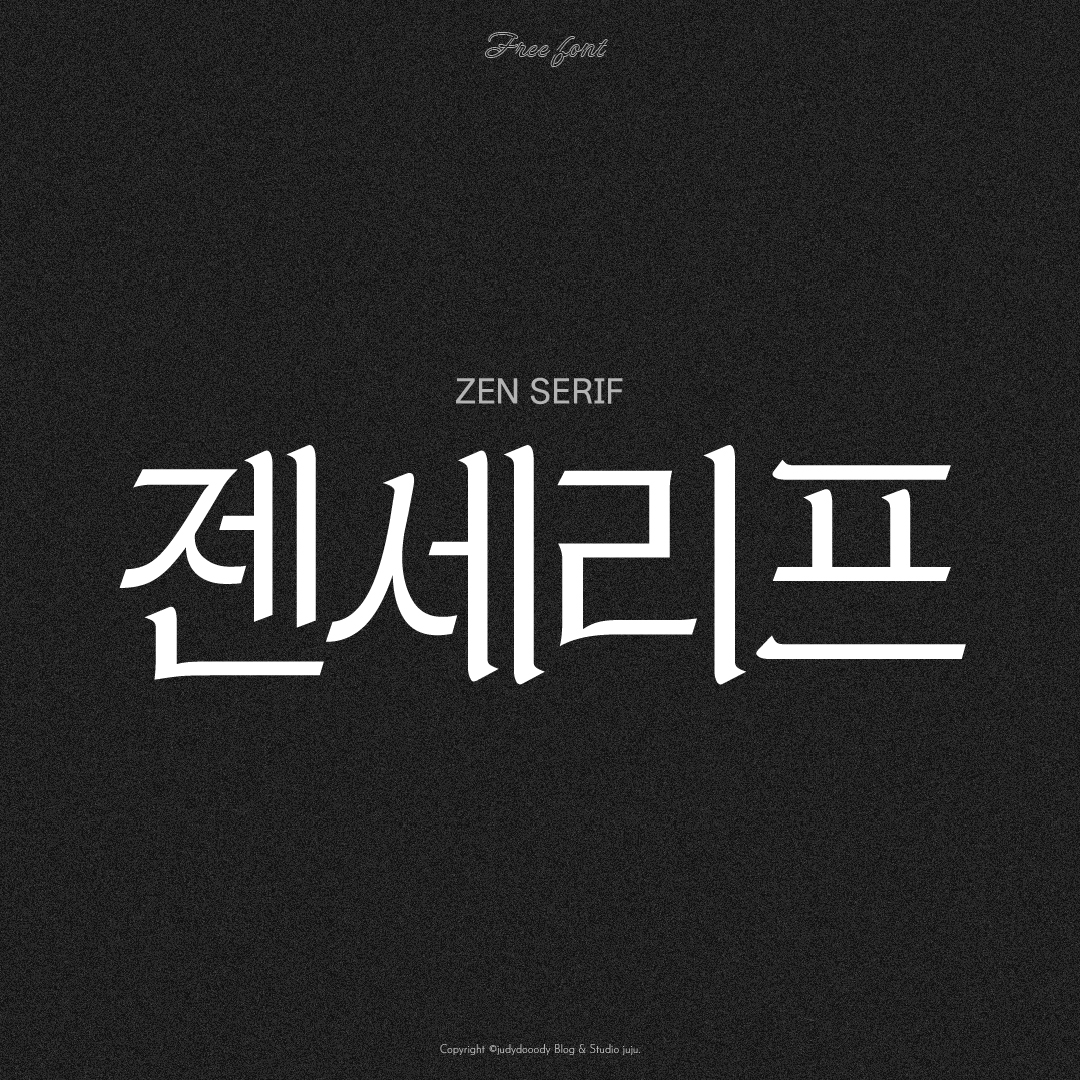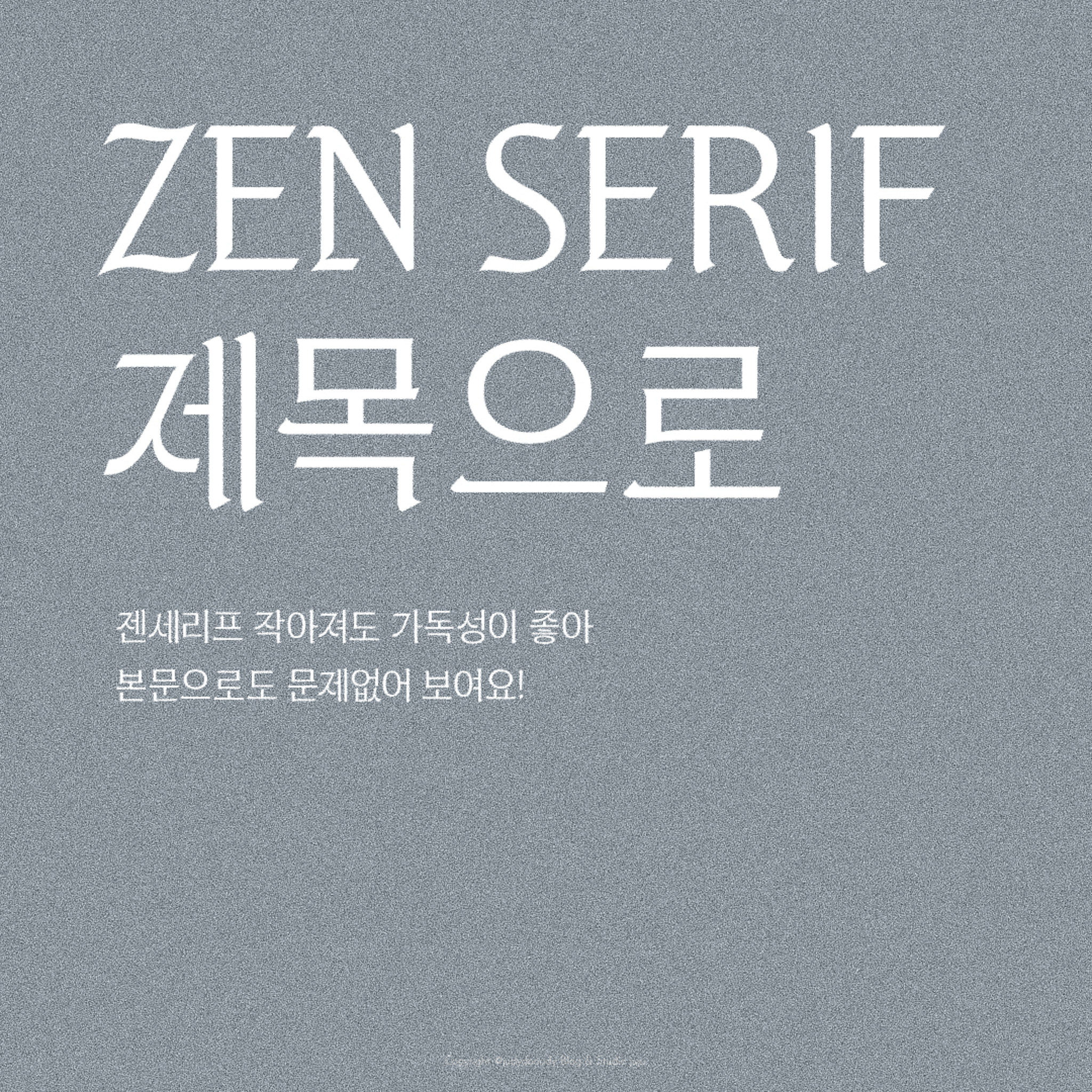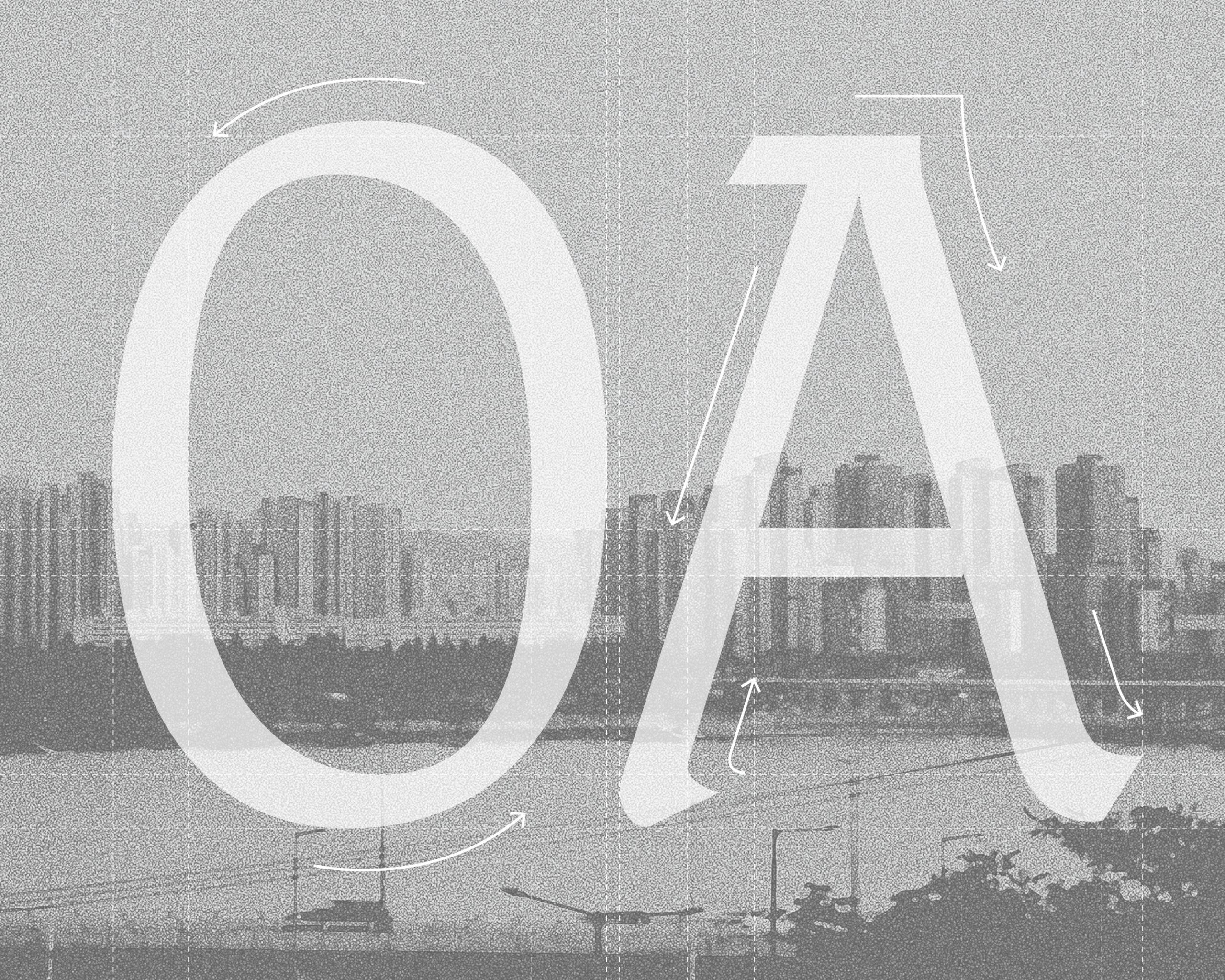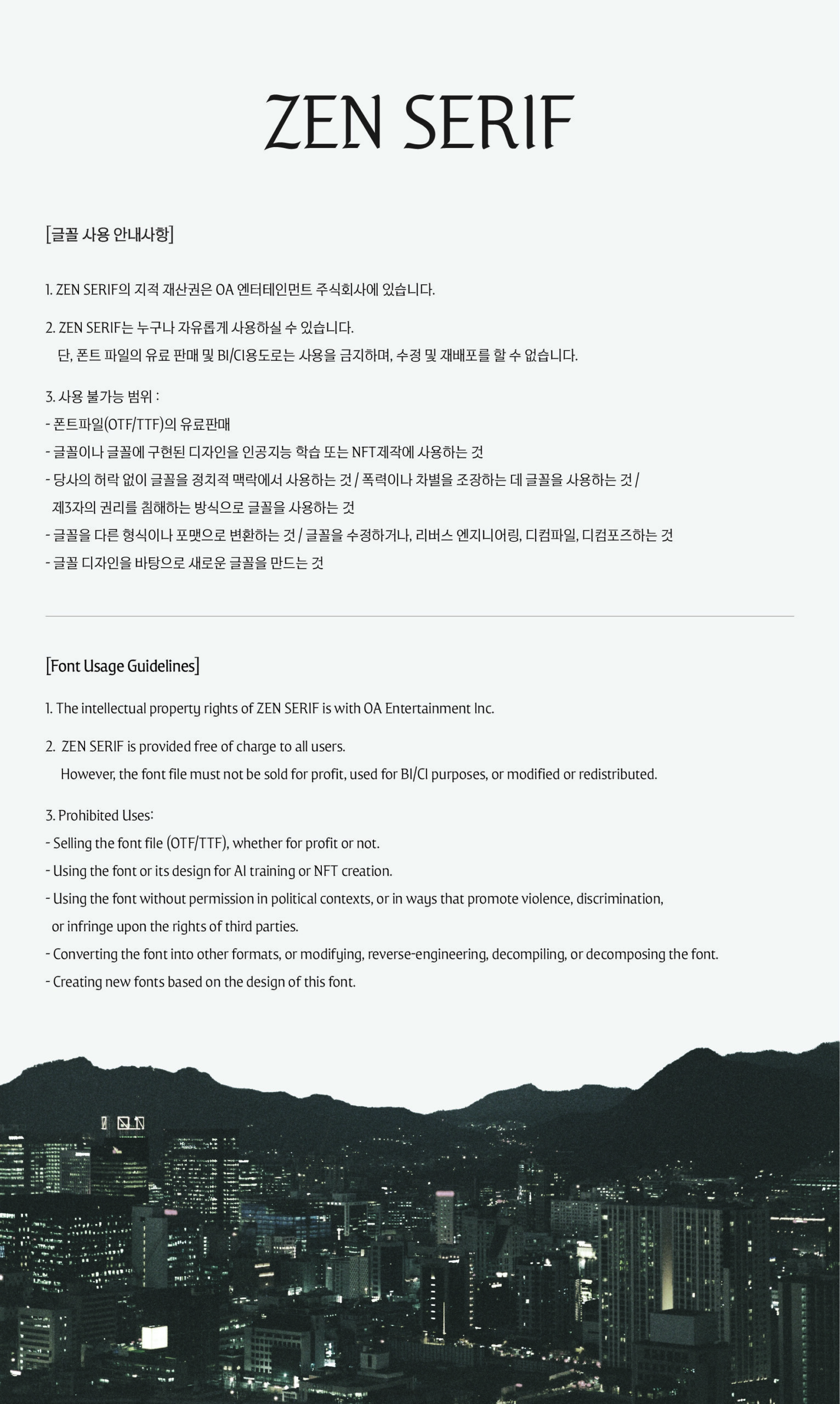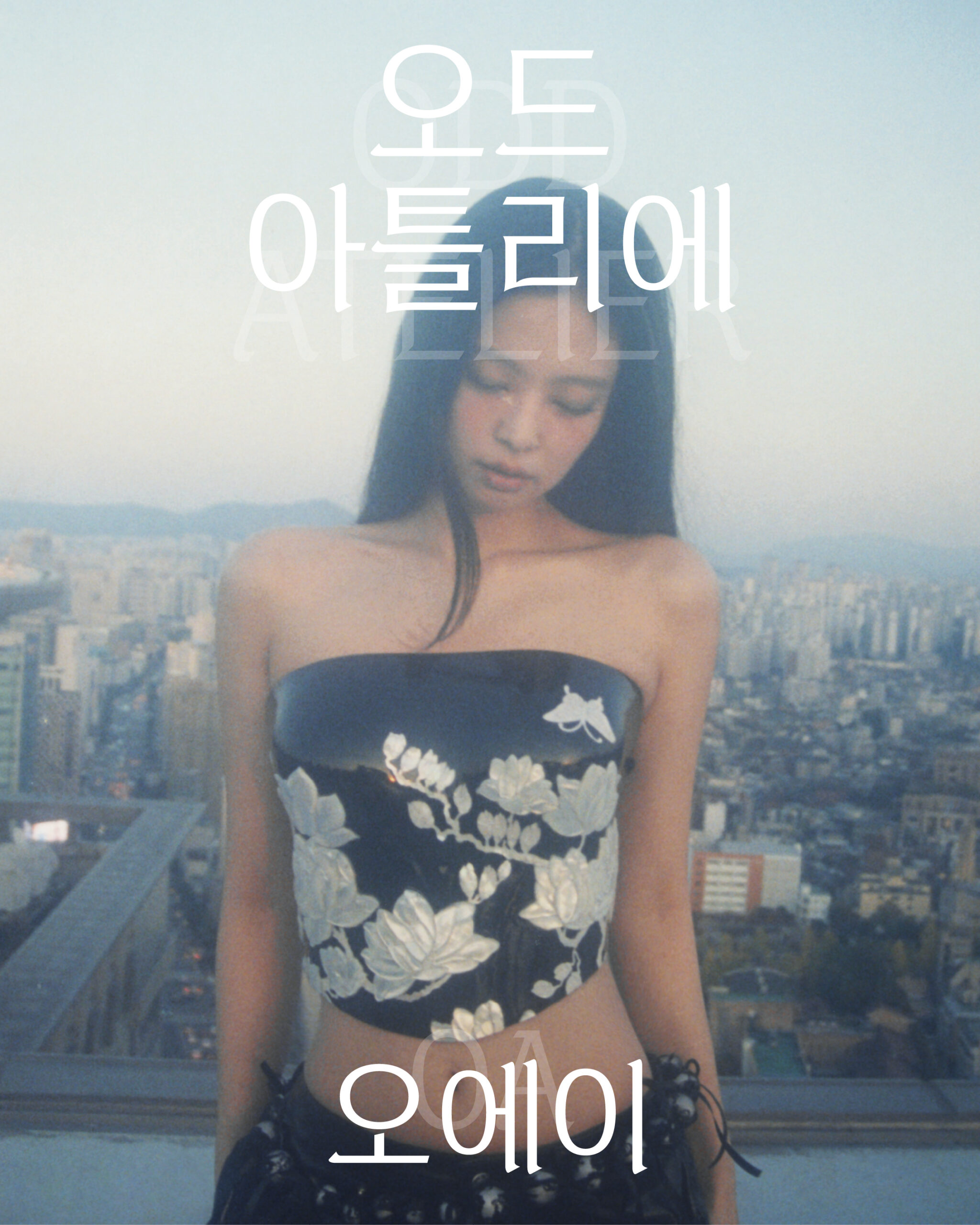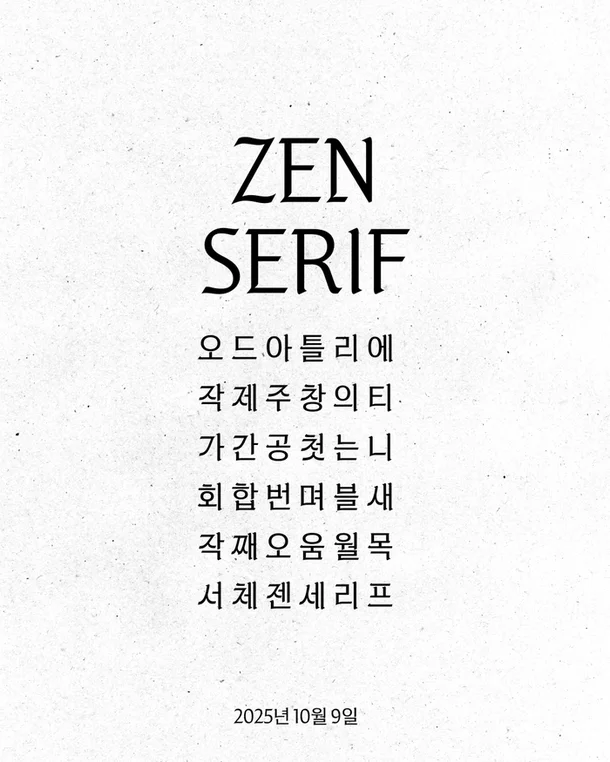
제니의 감성이 담긴 서체, 젠세리프(ZEN SERIF)
아티스트 제니(JENNIE)가 설립한 레이블 Odd Atelier에서
한글날을 기념해 특별한 서체 ZEN SERIF를 배포했어요.
놀랍게도, 연예기획사에서 서체를 공개한 건 처음이라고 하는데요!
'제니가 서체를?' 하는 물음표였는데,
직접 다운로드하여 사용해 보니 매력적인 디자인이에요.
젠세리프는 세종대왕이 한글을 창제한 정신,
즉 누구나 쉽게 글자를 배우고 쓸 수 있게 하려는 철학을 이어받아
글로벌 팬들에게 한글의 아름다움과 가치를 알리기 위해 제작되었다고 해요.
블랙레터 기반이지만 장식 요소는 배제해
오히려 현대적인 세리프체의 미감이 느껴져요.
세리프 Serif, 부리
강조용, 제목용, 본문용
약간 낯설 수도 있지만,
자세히 보면 묘하게 익숙하고 감성적인 매력이 있어요.
블랙레터를 기반으로 하되,
과한 장식 없이 절제된 디자인이라서
포스터, 타이틀, 굿즈 등 다양한 곳에 부담 없이 활용할 수 있는 서체예요.
특히, ‘ㅇ’의 형태가 크게 디자인되어
부드럽고 따뜻한 인상도 느껴진답니다.
덕분에 감성적인 무드의 콘텐츠에 포인트로 넣기에도 딱 좋아요.
또한, 메타(Meta)와 협업으로 SNS에서도 사용할 수 있도록
Edits 앱에도 한글폰트를 최초로 등록했다고 하니,
Edits 앱을 통해서도 ZEN SERIF를 즐겨보시면 좋을 것 같네요!